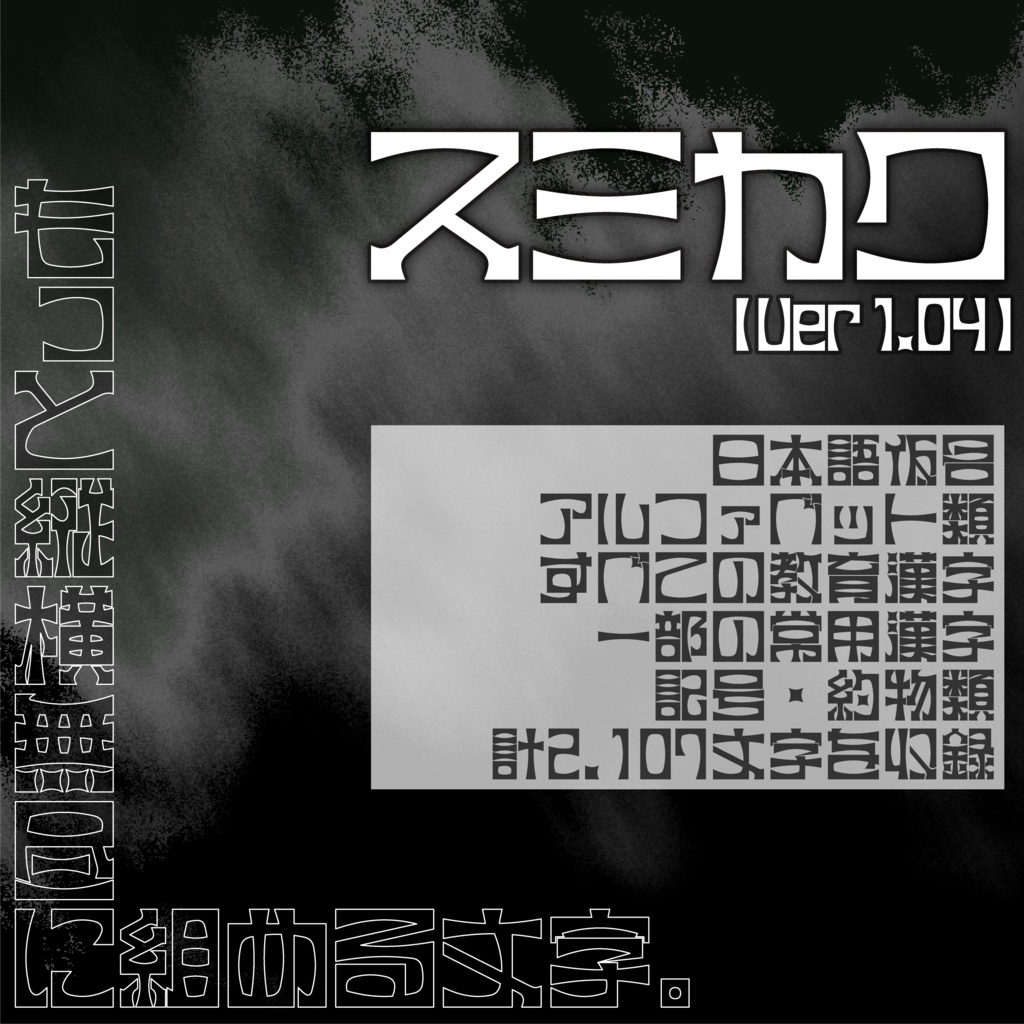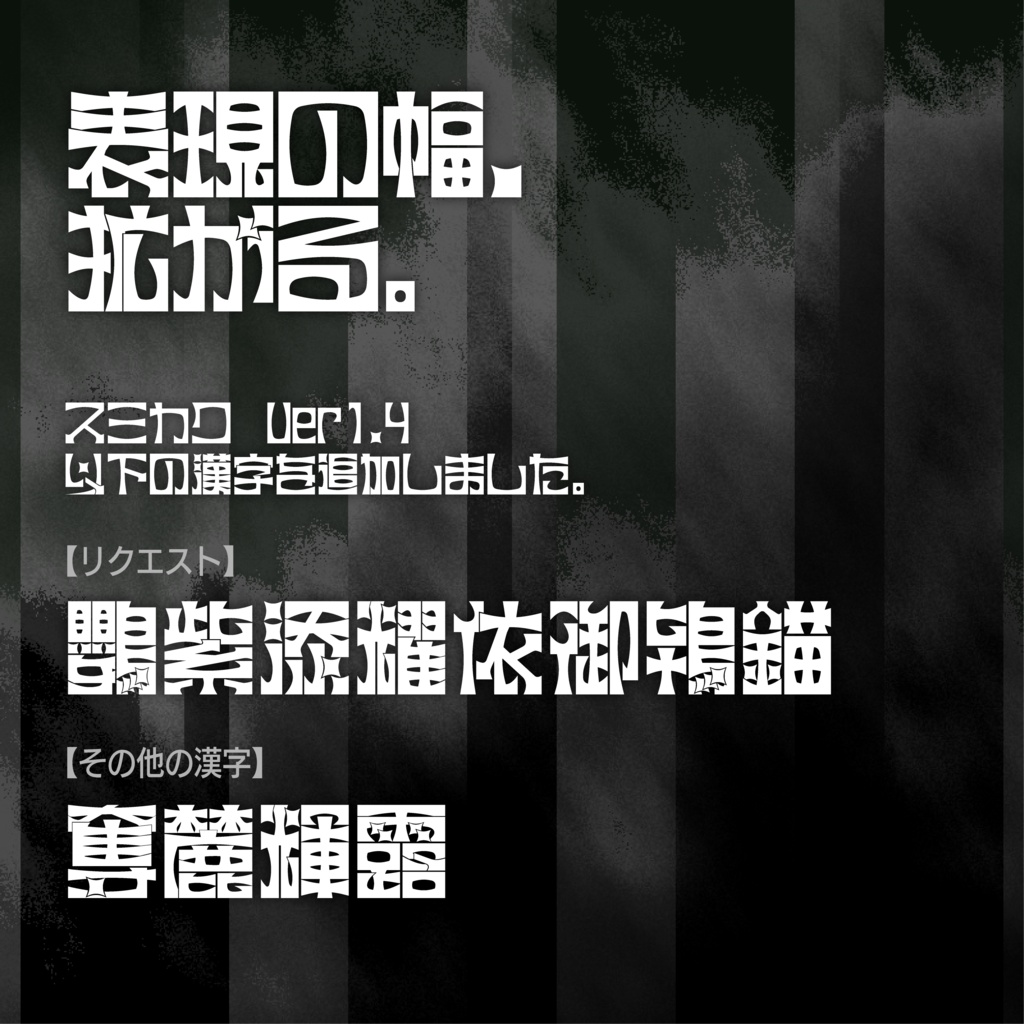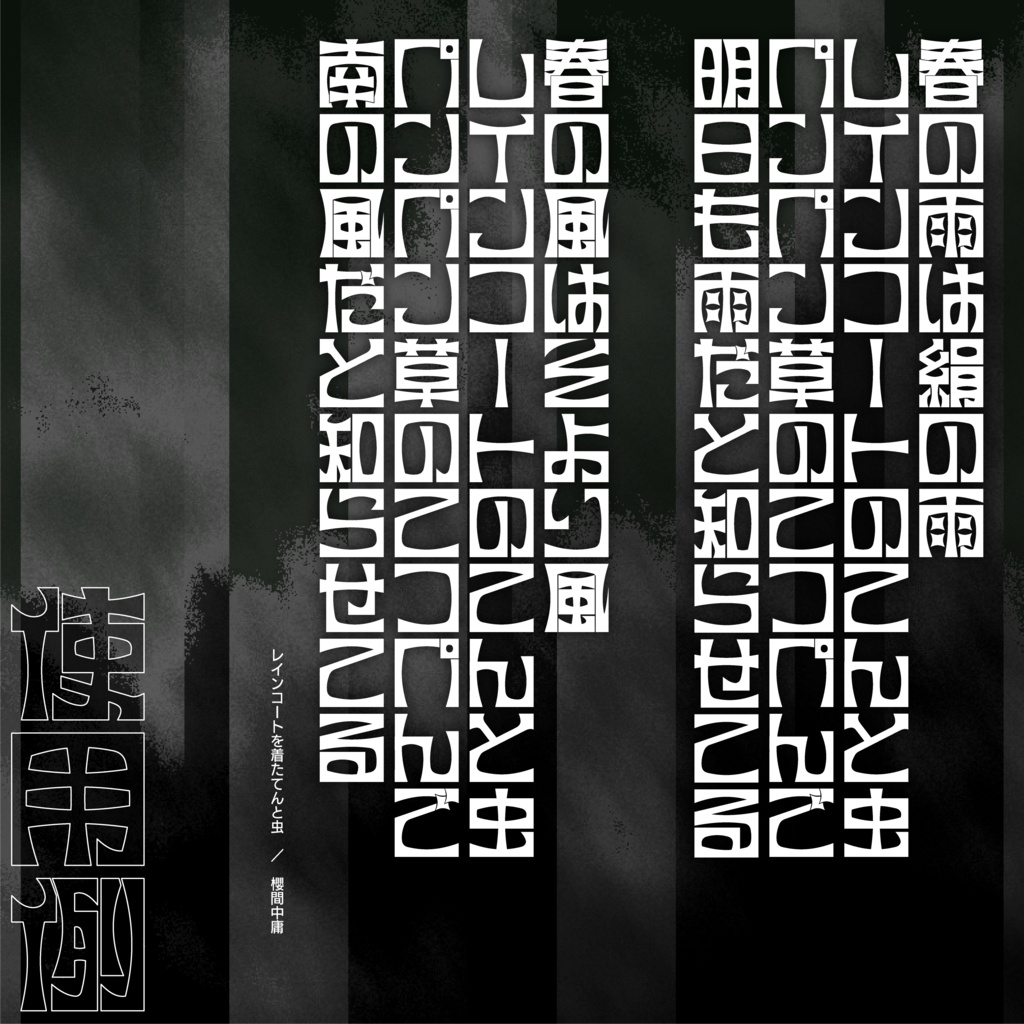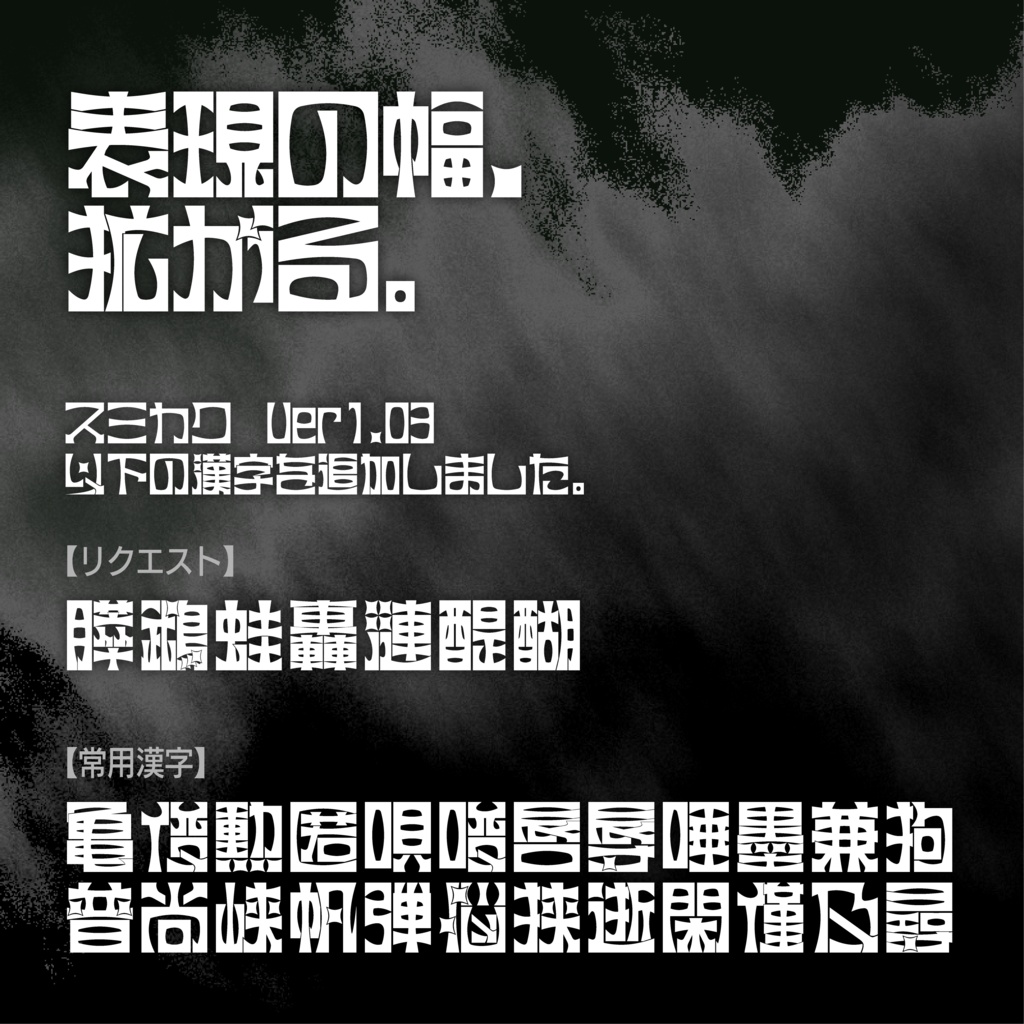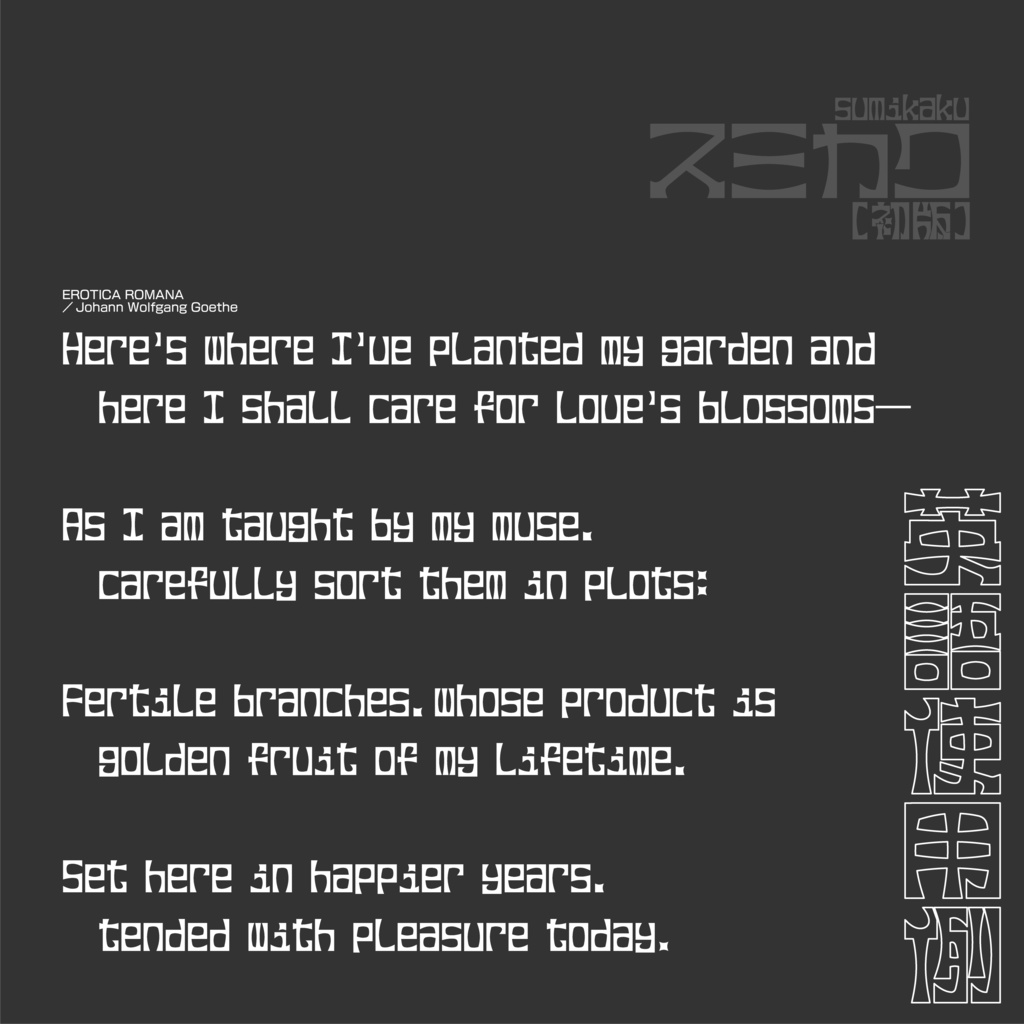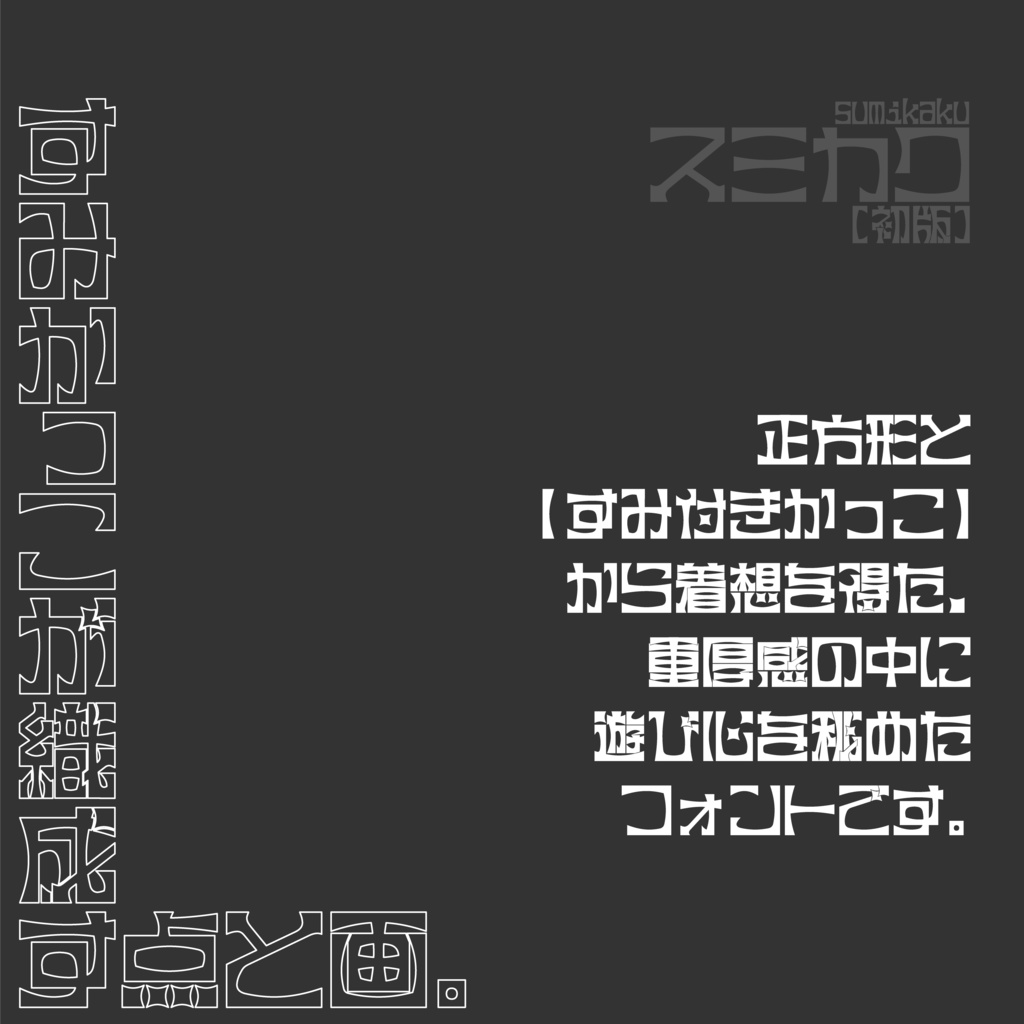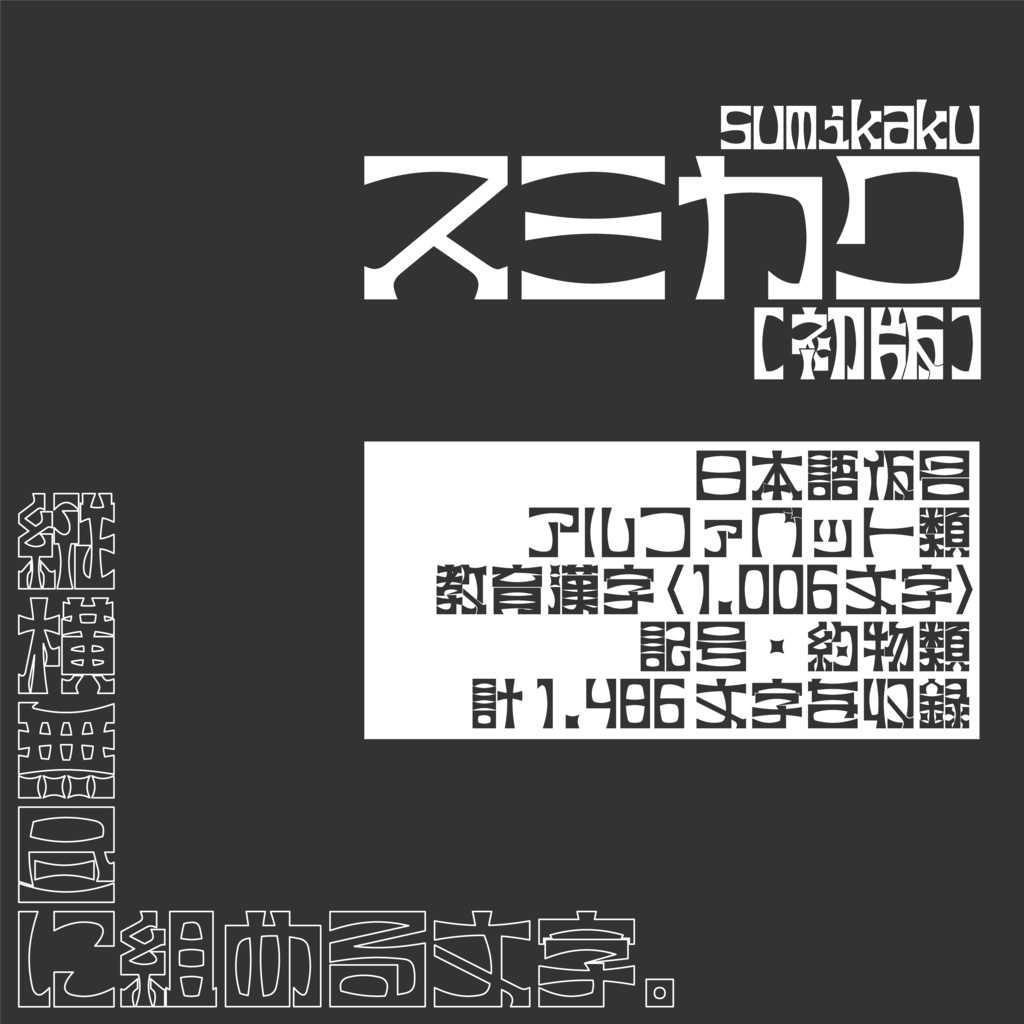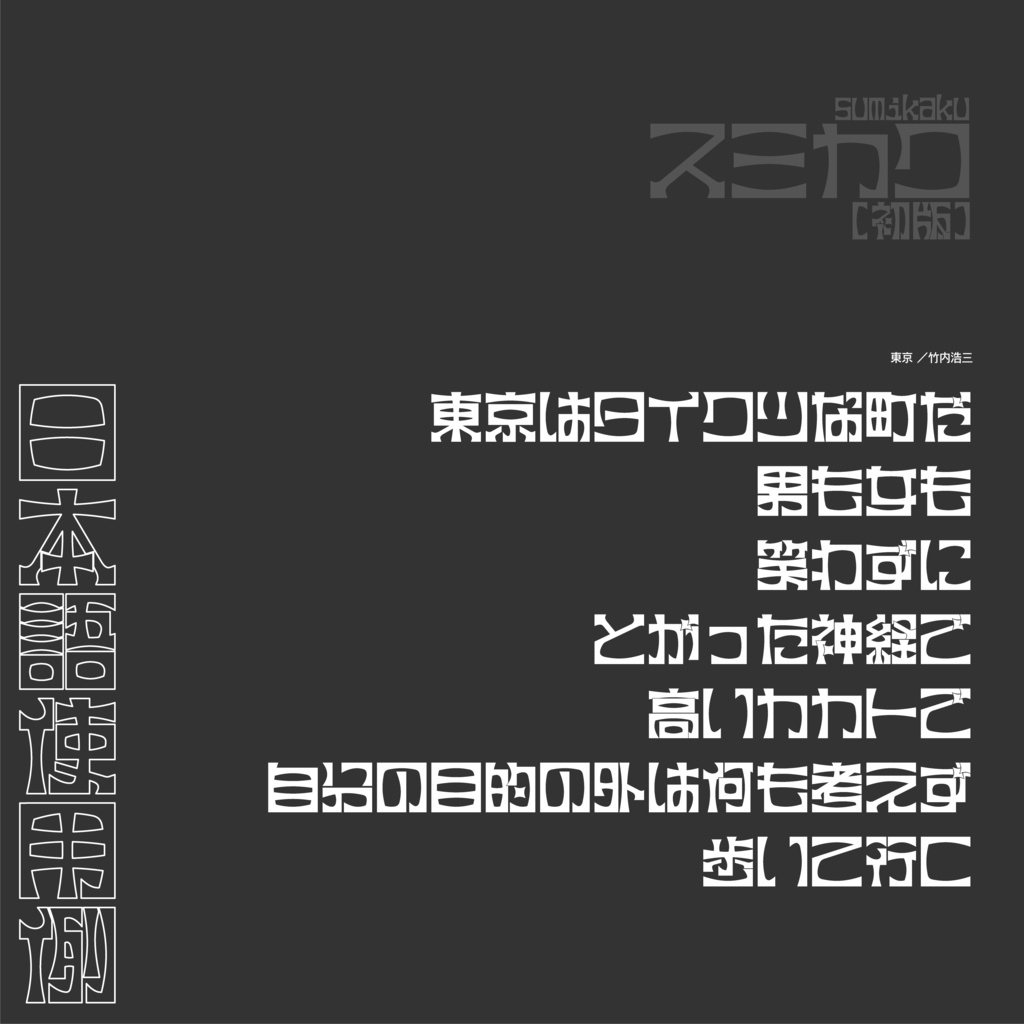
フリーフォント スミカク【Ver1.04】
■「スミカク」について フリーフォント「スミカク」です。 「スミカク」は、正方形をベースに、隅付き括弧(【 】)を彷彿とさせるユニークな点画を組み込んだデザインフォントです。あえて窮屈に収まるような独特の造形により、一文字一文字が強い実在感を放ちます。 ロゴ制作やフライヤーの大見出しなど、見る人に一瞬でインパクトを与えたい場面に最適です。 ※ご覧のフォントは、2026年9月20日にリリースされた「スミカク【Ver1.04】」となります。日本語仮名・アルファベット類と教育漢字、一部の常用漢字と表外漢字、記号・約物類の計2,107文字を収録しています。 ■収録文字 ・日本語仮名(ひらがな・カタカナ/濁音、半濁音、拗音、促音を含む) ・英数字および記号・約物類(一部約物は縦組みに対応) ・漢字:すべての教育漢字と常用漢字、一部表外漢字 1,618文字 ※収録文字は今後のアップデートにより追加予定です。詳細は以下のページをご覧ください。 https://busy-meteor-107.notion.site/365fe592ded580d8a5fbf06c66187487 ■【支援版購入者向け】漢字リクエストについて BOOTHにて支援版(¥200)をご購入いただいた方向けに漢字リクエストを実施します。 特に、「常用漢字ではない漢字」や「人名で使われる漢字」など、みなさまが『この文字がスミカクにあれば使いたい!』と感じている文字があれば、ぜひお聞かせください。今後のアップデートで追加する予定です。 詳細は以下の募集フォームをご覧ください。 https://forms.gle/Pbadwsbgu9DcdQQa8 ■利用にあたって この商品はフリーフォントです。原則、個人・商用問わず、どなたでも無償で使用することが可能です。フォントをインストール後は、ご自身の端末にて印刷物の作成や映像制作、Web等の媒体、ロゴデザイン等の制作などに利用できます。 商用時の連絡は特段不要です。もちろんご報告いただければよろこんで拝見します。 デザインに合わせたグリフの加工や変形はご自由に行なっていただけます(変形や分解、反転、比率変更、色変更なども可)。 なお、このフォントはオープンソースではないため、許可なくフォントデータを改変したり、再配布を行なったりすることを禁じます。 また、公序良俗に反する目的での利用はお控えください。 ■免責事項 本フォントの使用により生じた損害やトラブルについて、制作者は一切の責任を負いかねます。あらかじめご了承ください。 ■お問い合わせ・ご連絡先 フォントの不具合(文字のまちがい、不体裁など)のご報告やご感想は下記XアカウントのDMまでお寄せください。また、制作物のご報告もお待ちしております(任意/事前・事後問わず)。 ・制作:はしご/小鳥遊 ・X -はしご(@HashiGo_Puffin):https://x.com/HashiGo_Puffin こちらは制作者の主たるアカウントです。こちらでは、フォントの制作状況やその他創作物の進捗報告、趣味といった雑多をポストしています。気になる方はご覧ください。(お問い合わせや報告、メンションやタグ付けをされる際は、こちらのアカウントにお願いいたします。) ・X -小鳥遊(@HashiGo_DesiGn):https://x.com/HashiGo_DesiGn こちらは制作者の渉外用アカウントです。こちらでは、制作した/制作に携わった作品の報告を行なっております。よろしければフォローをお願いいたします。 ・過去の制作物:https://posfie.com/@HashiGo_Puffin/p/ZQ6qk9F ■ おことわり 一部の文字において描画の不均衡や調整不足など、至らない点が残っている可能性があります。 今後、アップデートを通じて修正・改善を行なっていく予定ではありますが、現状の品質についてあらかじめご了承いただいた上で、ご活用いただけますと幸いです。 ■ 更新履歴 2026/09/20 漢字を追加(v1.04) 2026/09/13 漢字を追加(v1.03) 2026/05/30 漢字を追加、一部グリフを再設計・修正(v1.02) 2026/04/10 一部グリフの不体裁を修正(v1.01) 2026/04/10 リリース(v1.00)